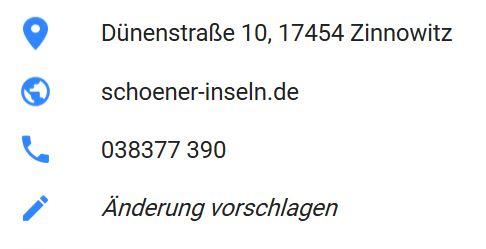
[Mitglied catf…] Geschrieben Juli 2, 2017 Teilen Geschrieben Juli 2, 2017 Ich sehe es mehrmals am Tag in leicht unterschiedlichen, aber dennoch einem sinntragenden Zeichen zuzuordnenden Form, jenes Zeichen, das eine geografische Position anzeigt, dass in Etwa so aussieht: Meine Frage nun, gibt es hierfür schon einen Unicode, und wenn ja, wie heißt dieses Zeichen dann genau. Und wenn nicht, sollte man es nicht für einen Unicode-Platz vorschlagen? Link zu diesem Kommentar
[Mitglied Chri…] Geschrieben Juli 2, 2017 Teilen Geschrieben Juli 2, 2017 Vielleicht irgendwas mit "Landmark" oder "Geo Position"? Edit: Oder einfach "Location"? Es gibt schon https://unicode-table.com/de/2316/ Position Indicator und https://unicode-table.com/de/2BD0/ Square Position Indicator. Link zu diesem Kommentar
[Mitglied catf…] Geschrieben Juli 2, 2017 Themen-Ersteller Teilen Geschrieben Juli 2, 2017 Es gibt zwar einen Position Indicator (U+2316) aber das ist ein ganz anderes Zeichen (Ein Kreis mit Fadenkreuz) Als Positioning Icon habe ich in der Bildersucht zig Belege für die Nutzung des Zeichens gefunden, uns damit irgendwie eine nahezu weltweite Übereinstimmung der Grundform - aber Unicode??? Ich könnte mir denken, dass dies eine größere Nutzung hätte, als ein "Pile oft Poo" Link zu diesem Kommentar
[Mitglied catf…] Geschrieben Juli 2, 2017 Themen-Ersteller Teilen Geschrieben Juli 2, 2017 Hier noch eine Testanwendung im Text: 1 Link zu diesem Kommentar
[Mitglied 3b3f…] Geschrieben Juli 2, 2017 Teilen Geschrieben Juli 2, 2017 Wenn du das Icon weglässt, ist es aber genauso verständlich. Für mich macht eine Marke im Text gar keinen Sinn, da es keinen Punkt gibt, der markiert werden kann. Link zu diesem Kommentar
[Mitglied catf…] Geschrieben Juli 2, 2017 Themen-Ersteller Teilen Geschrieben Juli 2, 2017 Ich habe mich eben mal durch die Unicode-Symbole gewühlt, und das Zeichen nicht gefunden. ein möglicher Platz (auf zig Pfeile folgend) und noch unbelegt wäre U+1F8AE. Nebenbei, für Telefon, Fax, und anderes werden ja auch Symbole aus den gewohnten Dingbats verwendet, die im Unicode zu finden sind, obwohl es eigentlich zumeist ohne verständlich ist. Noch ein Beispiel: Link zu diesem Kommentar
[Mitglied Robe…] Geschrieben Juli 2, 2017 Teilen Geschrieben Juli 2, 2017 vor einer Stunde schrieb bertel: Für mich macht eine Marke im Text gar keinen Sinn, da es keinen Punkt gibt, der markiert werden kann. schnellere erfassbarkeit beim überfliegen des textes? ich empfinde das zeichen nicht als störend, fügt sich doch harmonisch ein. kommt aber sicher auf den context an. Link zu diesem Kommentar
[Mitglied 3b3f…] Geschrieben Juli 2, 2017 Teilen Geschrieben Juli 2, 2017 In einer Tabelle (wie von catfonts danach gepostet) ja, aber im Fließtext bringt mir das keinen Mehrwert. Zumal die Ortsangabe in Koordinaten selbst nicht gerade unauffällig ist. Link zu diesem Kommentar
[Mitglied catf…] Geschrieben Juli 2, 2017 Themen-Ersteller Teilen Geschrieben Juli 2, 2017 Das hab ich ja hauptsächlich gemacht, um das Zeichen mit dem Text zusammen zu zeigen, egal ob das in diesem Fall nötig ist. Einfach nur mal, wie sich das im Font macht… Link zu diesem Kommentar